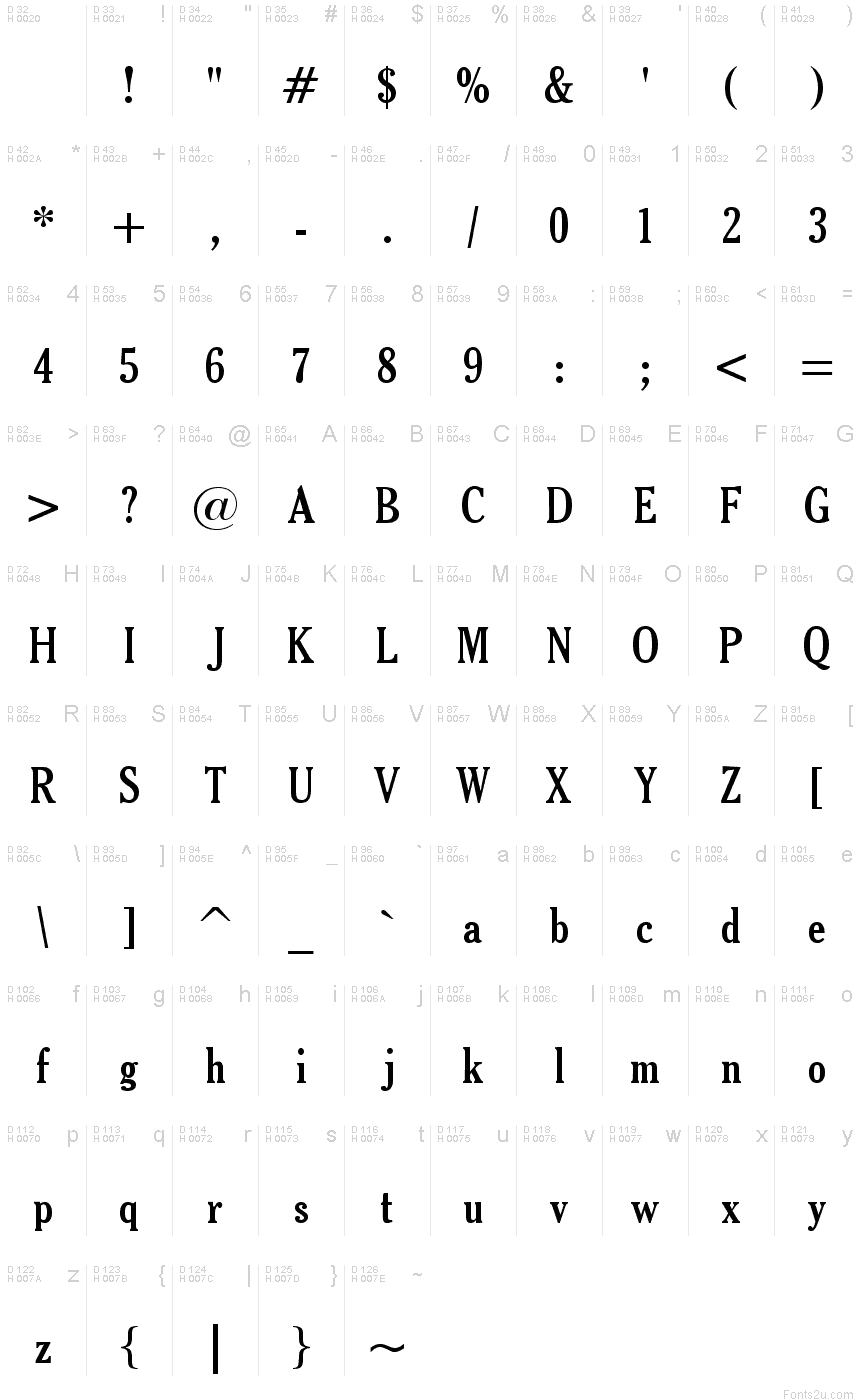
Thyssen J
يعد خط Thyssen J من Immortalware خطاً مجانياً بزوائد (Serif) يتمتع بحضور جريء يكاد يكون معمارياً. الضربات الرأسية السميكة والمسافات المتقاربة والزوائد الإسفينية تمنحه طابعاً قوياً يشبه "الحبر على الورق"، وكأنه مقتبس من عنوان صحيفة عتيقة. هناك انحناء ومرونة دقيقة في الأشكال تمنع الخط من الشعور بالجمود، مما يجعله يقع في منطقة وسطى بين فن طباعة الكتب الكلاسيكي وقوة الخطوط الصناعية العريضة.
مع Thyssen J، ستحصل على خط بزوائد يفرض حضوره دون صخب، مما يجعله خياراً طبيعياً للشعارات، وأغلفة الكتب، والملصقات، والعناوين التحريرية، وقوائم الطعام، وتصاميم التغليف ذات الطابع التراثي. يتألق هذا الخط المجاني عند استخدامه بأحجام كبيرة، حيث تبرز تفاصيله القوية وإيقاعه المميز، كما يتناغم بشكل خاص مع خطوط هندسية بلا زوائد (Sans Serif) للنصوص الفرعية.